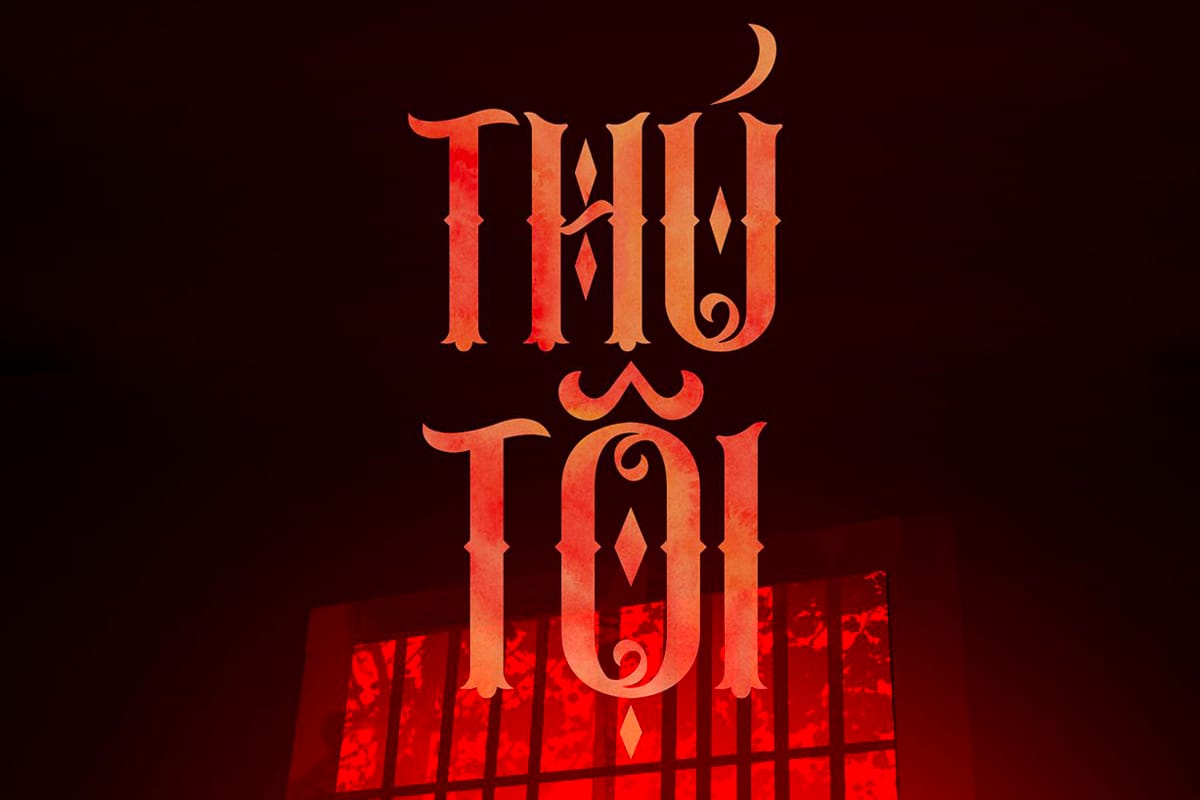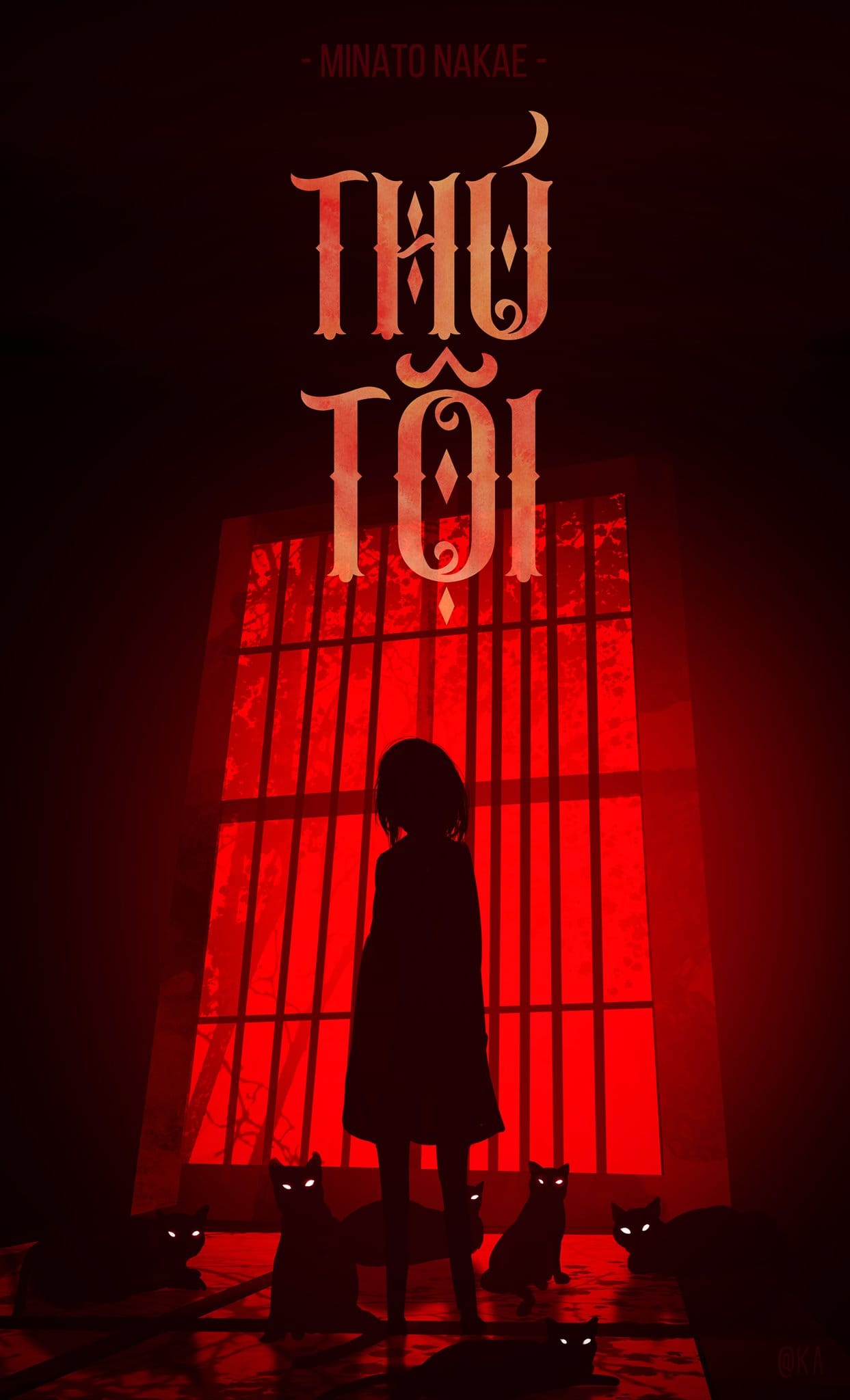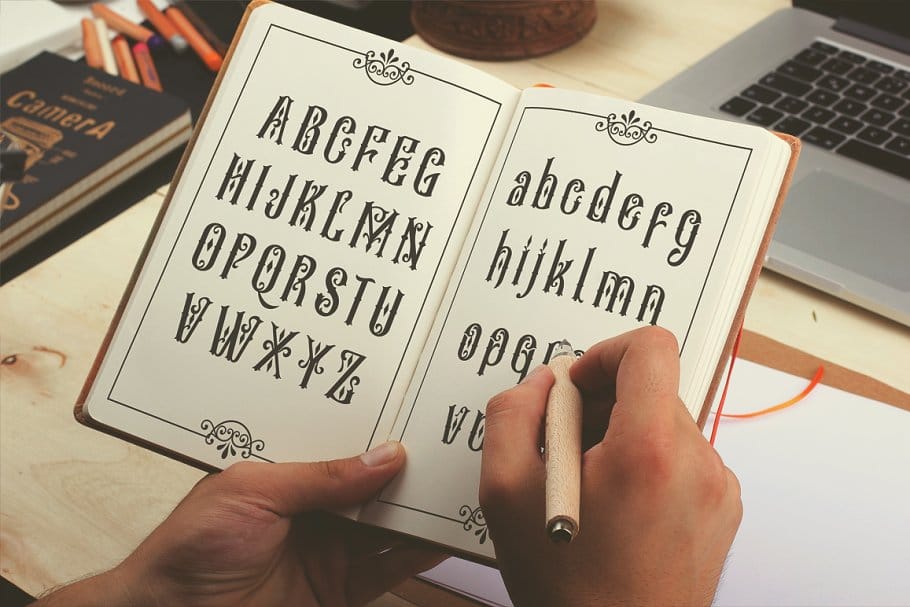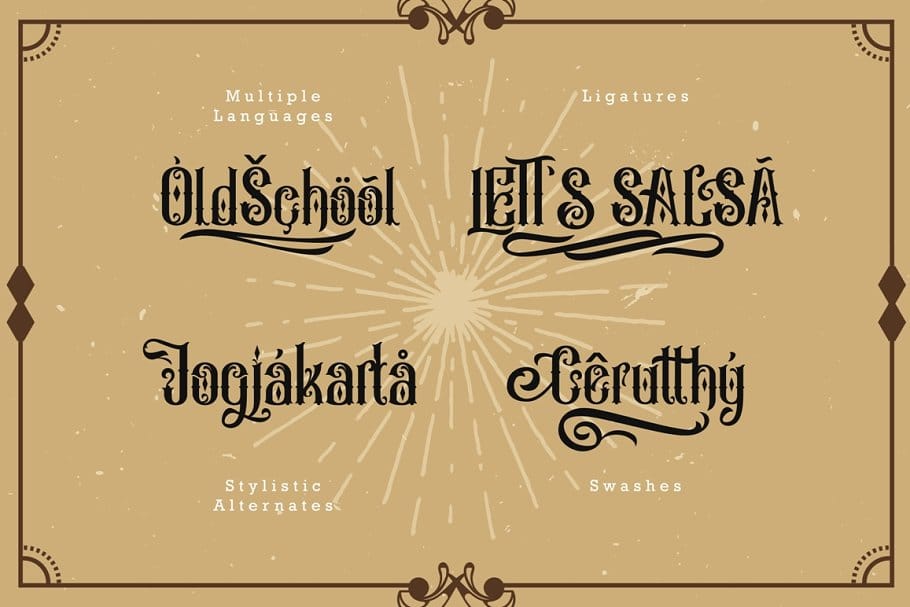
Font Besigetz Việt Hóa – Kiểu font cổ điển
Xin chào các bạn! Giới thiệu đến các bạn 1 font Besigetz Việt Hóa mới với ý tưởng cổ điển mang lại nhiều ấn tượng. Các chữ cái được tạo theo phông chữ serif cơ bản. Tôi khuyên bạn nên thử cái này cho dự án thiết kế của mình, đặc biệt là theo phong cách cổ điển, retro hoặc oldschool! Ngoài ra, bạn có thể thực hiện thử nghiệm của mình bằng cách kết hợp kiểu chữ này với phong cách hiện đại hoặc tối giản.